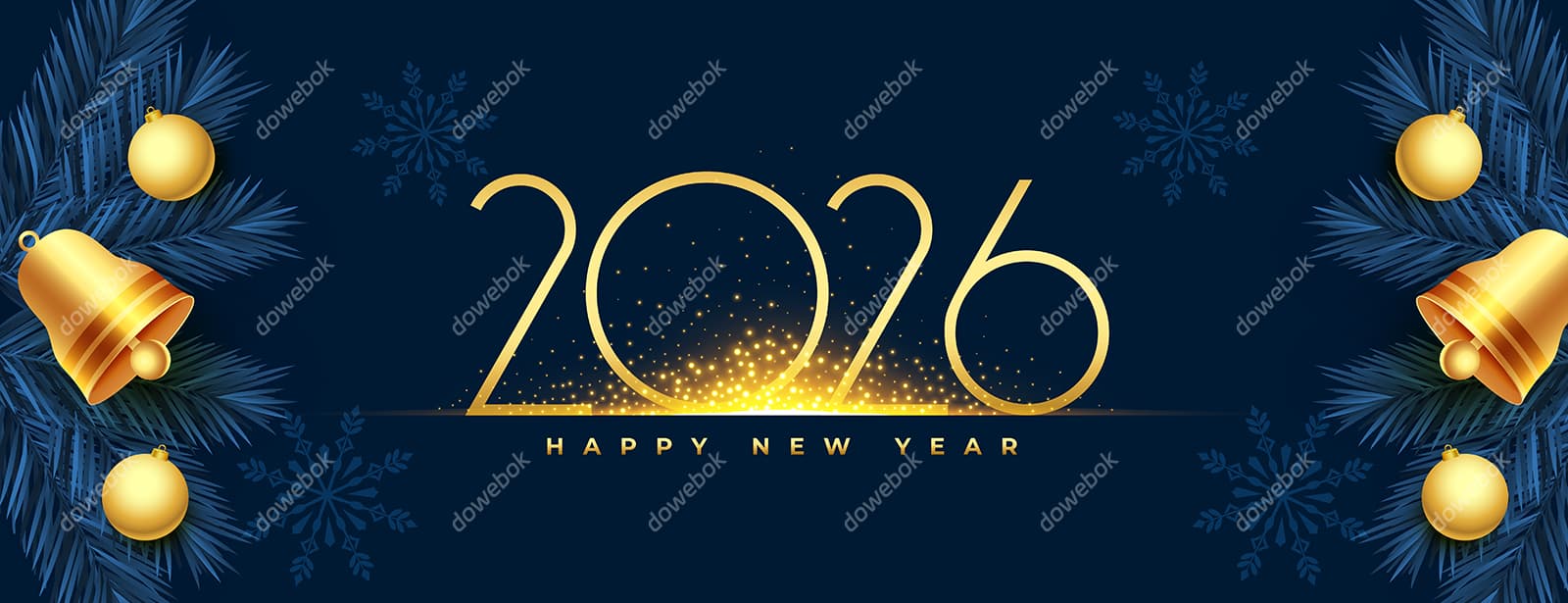
这是一款金色铃铛和数字设计的 2026 新年快乐矢量素材,深幽藏蓝背景衬着雪花暗纹,两侧蓝松枝搭配金铃、金球,还原冬日节庆装饰氛围。鎏金 “2026” 字体间缀着细碎金芒,下方 “Happy New Year” 字样简约呼应。整体以蓝金配色融合圣诞新年元素,既显冬日节日的雅致格调,又用金属装饰细节透出温馨的仪式感,清冷中裹着暖意。